Font chữ Trung Quốc không chỉ giúp hiển thị ký tự mà còn mang giá trị thẩm mỹ, gợi dấu ấn văn hóa Á Đông. Từ thư pháp cổ điển đến phong cách hiện đại, những font này ngày càng phổ biến trong học tập và thiết kế. Bài viết sẽ giới thiệu Top 10+ font chữ Trung Quốc đẹp, miễn phí để bạn dễ dàng tải về và ứng dụng ngay.
Ứng dụng của font chữ tiếng Trung
- Thiết kế & in ấn: Font tiếng Trung được dùng trong logo, bao bì, poster phim, bảng hiệu để tạo điểm nhấn và truyền tải nét Á Đông đặc trưng.
- Học tiếng Trung: Người học dễ dàng nhận diện mặt chữ, luyện viết và ghi nhớ khi dùng font chuẩn.
- Truyền thông số: Trong social media, nhiều bạn trẻ sử dụng font Trung Quốc để tạo caption, story hoặc art typography mang phong cách mới lạ.
- Mỹ thuật & thư pháp: Font mô phỏng chữ viết tay, thư pháp cổ được ứng dụng nhiều trong thiết kế văn hóa, sách báo hoặc ấn phẩm trang trọng.
Kết hợp font Trung Quốc với màu sắc, layout để ra thiết kế đẹp
Một font chữ đẹp sẽ càng nổi bật khi kết hợp với màu sắc và bố cục hợp lý. Ví dụ, font thư pháp Trung Quốc thường đi cùng tông màu đỏ, đen hoặc vàng để gợi nét truyền thống và sang trọng. Trong khi đó, font hiện đại nên kết hợp với màu pastel hoặc gradient để mang cảm giác trẻ trung. Layout cũng đóng vai trò quan trọng: chữ nên có khoảng trắng thoáng, tránh sắp xếp quá dày gây khó đọc.
Bộ sưu tập 10+ font chữ Trung Quốc đẹp và phổ biến
Font Chinese Calligraphy
Đây là font mô phỏng bút lông thư pháp truyền thống, mang hơi thở cổ điển và tinh thần văn hóa Trung Hoa. Rất phù hợp cho poster, tranh chữ, hoặc thiết kế liên quan đến nghệ thuật và phong thủy.
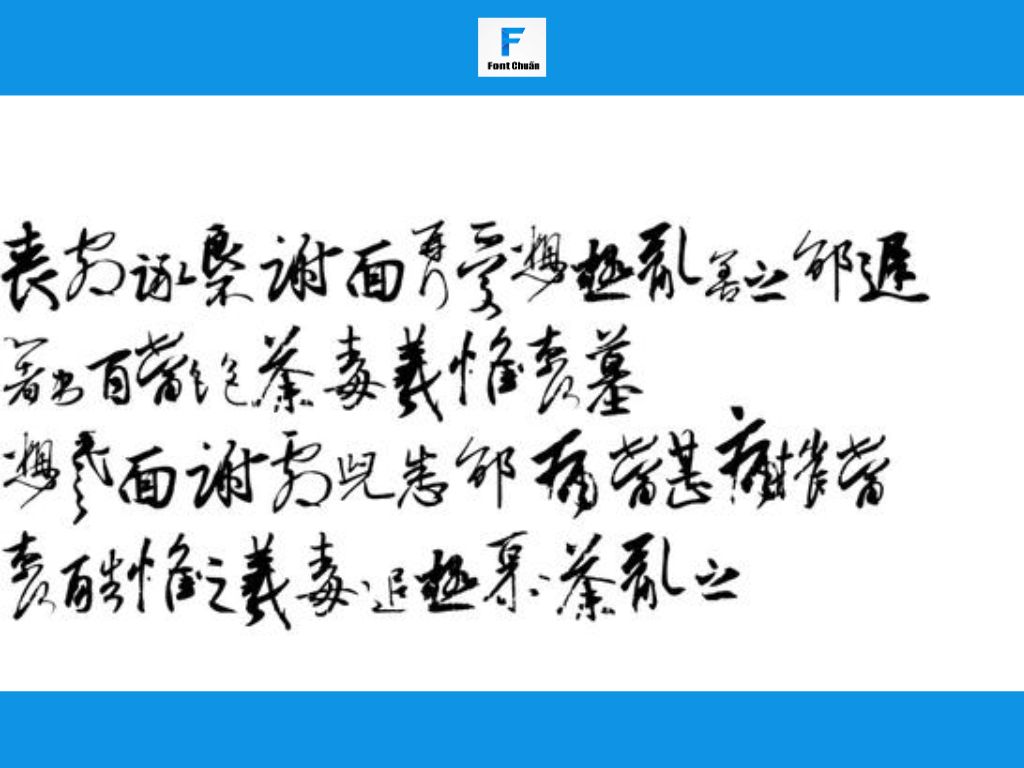
Font Noto Sans SC
Thuộc dự án Google Fonts, Noto Sans SC mang phong cách tối giản, rõ ràng và dễ đọc. Thường được dùng trong giao diện website, app, hoặc tài liệu học tiếng Trung.
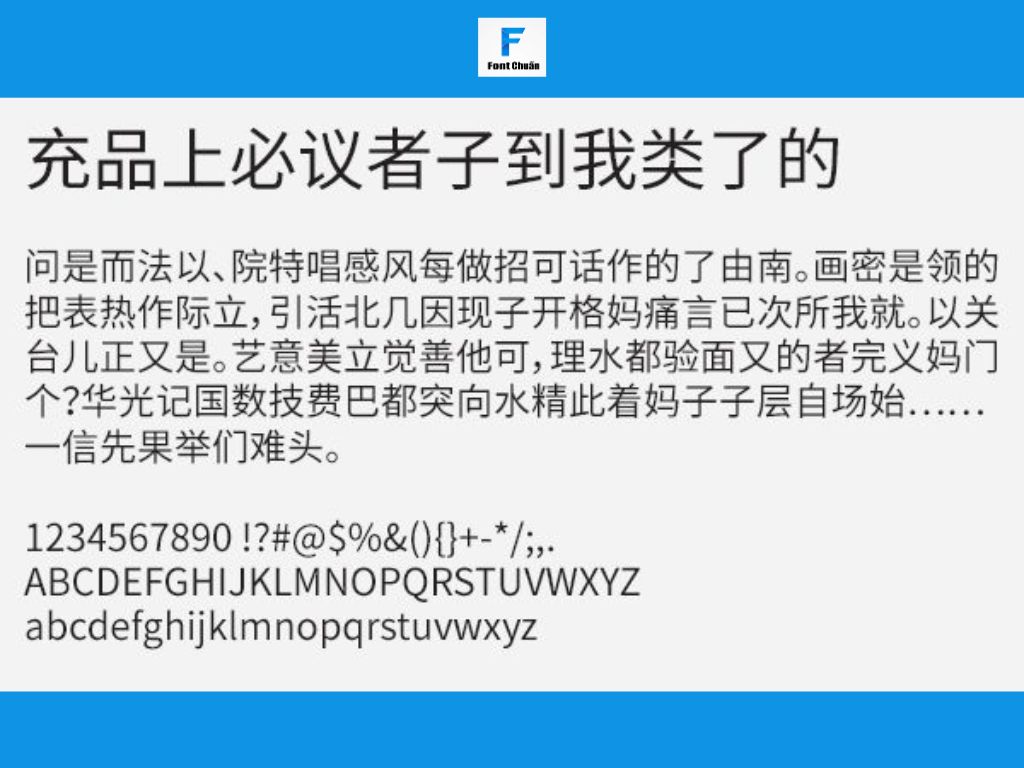
Font SimHei
SimHei là font chữ in đậm phổ biến trong tiếng Trung, mang lại cảm giác mạnh mẽ và chắc chắn. Font này hay được dùng trong tiêu đề báo, bảng quảng cáo hoặc thiết kế cần nhấn mạnh.
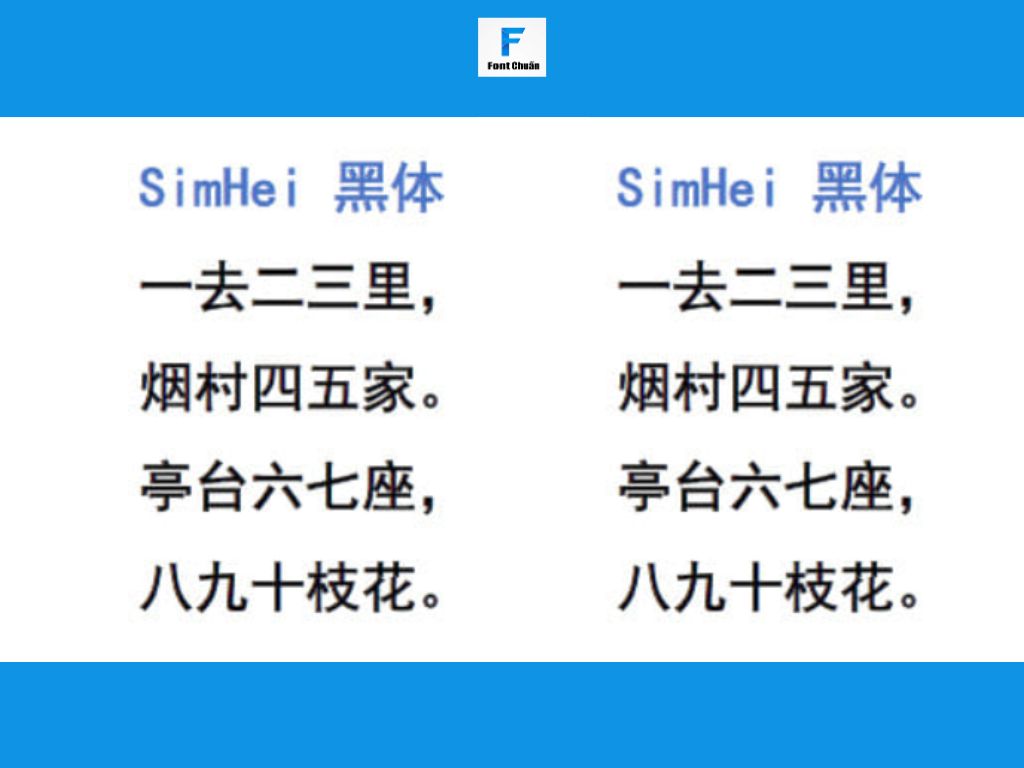
Font KaiTi
KaiTi được lấy cảm hứng từ thư pháp bút lông với nét chữ uyển chuyển nhưng vẫn dễ đọc. Nó thường xuất hiện trong sách giáo khoa, tài liệu học tập và các ấn phẩm mang tính học thuật.
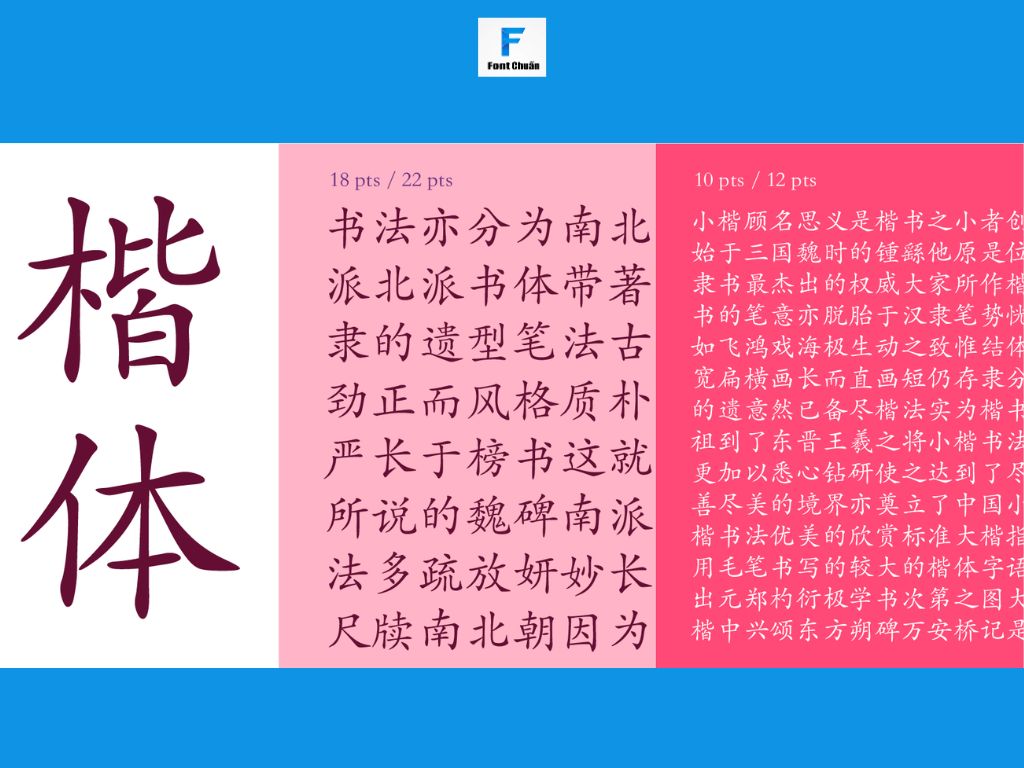
Font FangSong
FangSong có nét chữ vuông vắn, cân đối, phù hợp với việc in sách, tạp chí hay các văn bản hành chính. Đây là một trong những font truyền thống lâu đời, gắn liền với văn hóa đọc Trung Hoa.
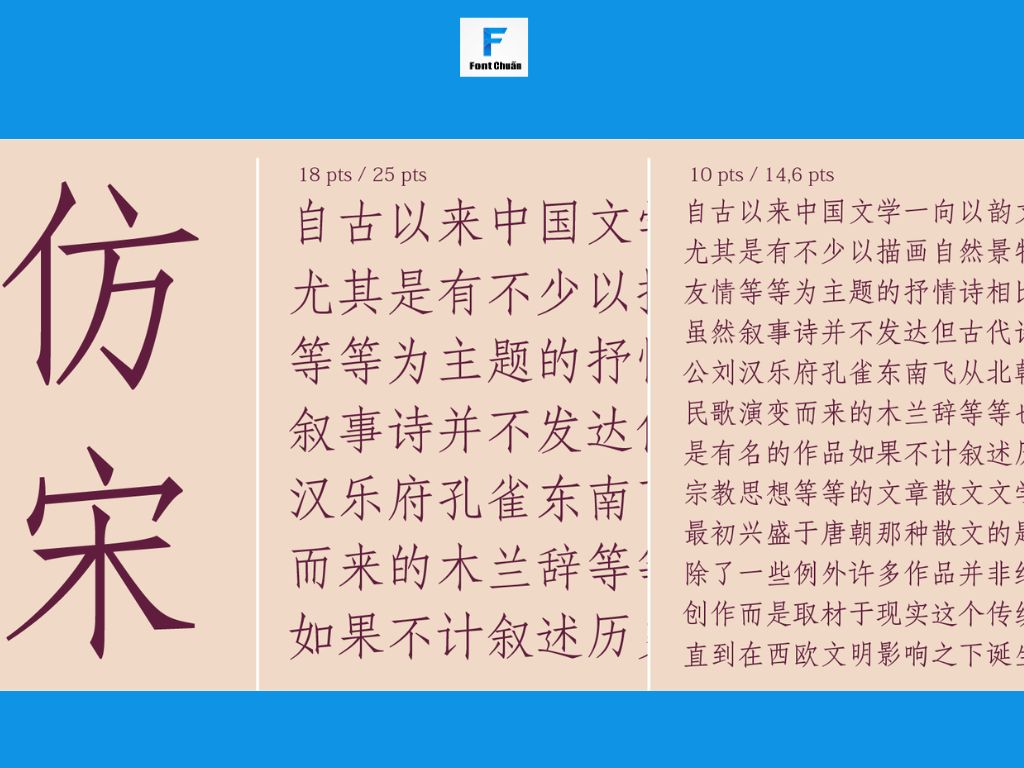
Font STXihei
STXihei mang hơi hướng hiện đại, tròn trịa và dễ nhìn. Font này thường được các designer trẻ ưa chuộng khi thiết kế poster, banner hoặc nội dung số.
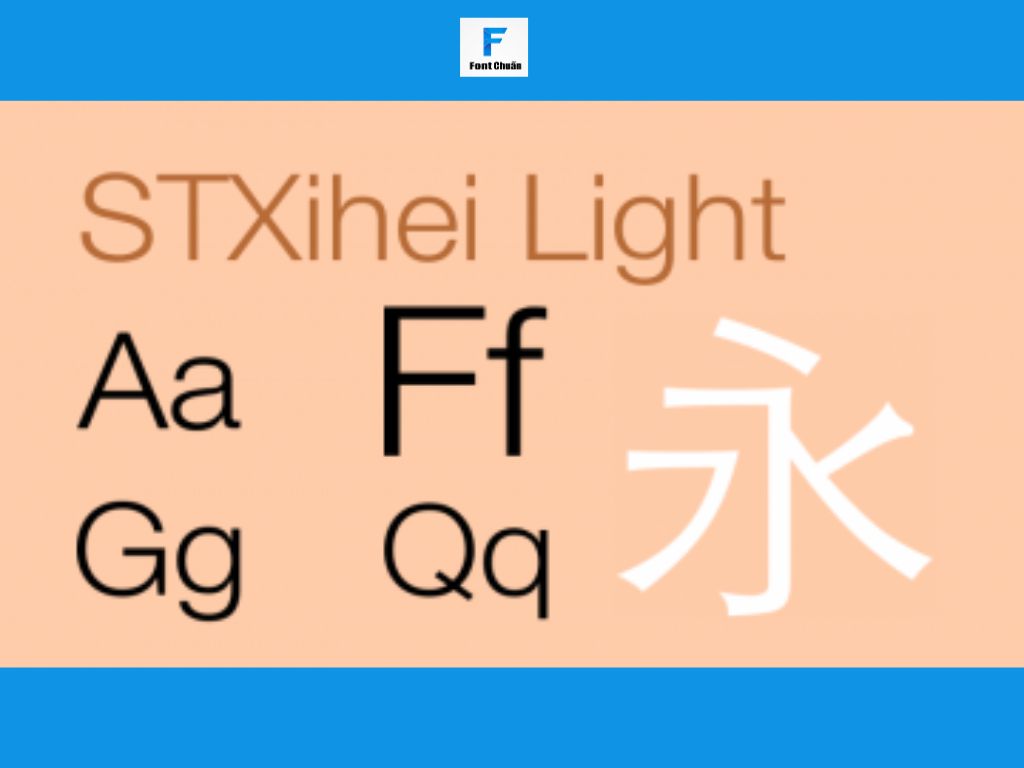
Font HanWangMing
HanWangMing có phong cách trang trọng, thường được sử dụng trong các tài liệu chính thức, biển hiệu hoặc ấn phẩm cần sự nghiêm túc. Các nét chữ rõ ràng, cứng cáp, thích hợp cho in ấn chất lượng cao.
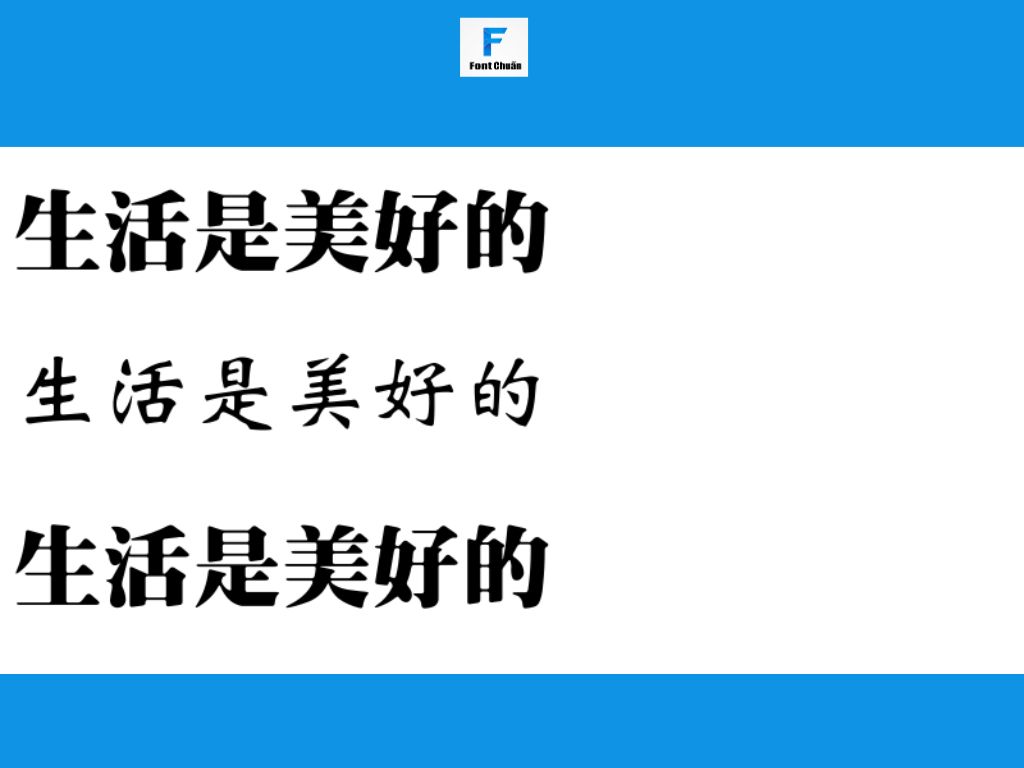
Font Zen Antique
Zen Antique là sự kết hợp giữa phong cách chữ Trung Hoa và Nhật Bản cổ điển. Font này thường dùng trong thiết kế nghệ thuật, truyện tranh lịch sử, hoặc sản phẩm gợi nhớ quá khứ.
Font Zhi Mang Xing
Đây là font thư pháp nghệ thuật với nét chữ bay bổng, mềm mại. Zhi Mang Xing thường được dùng cho thiệp mời, tranh chữ, hoặc thiết kế mang tính cảm xúc, lãng mạn.
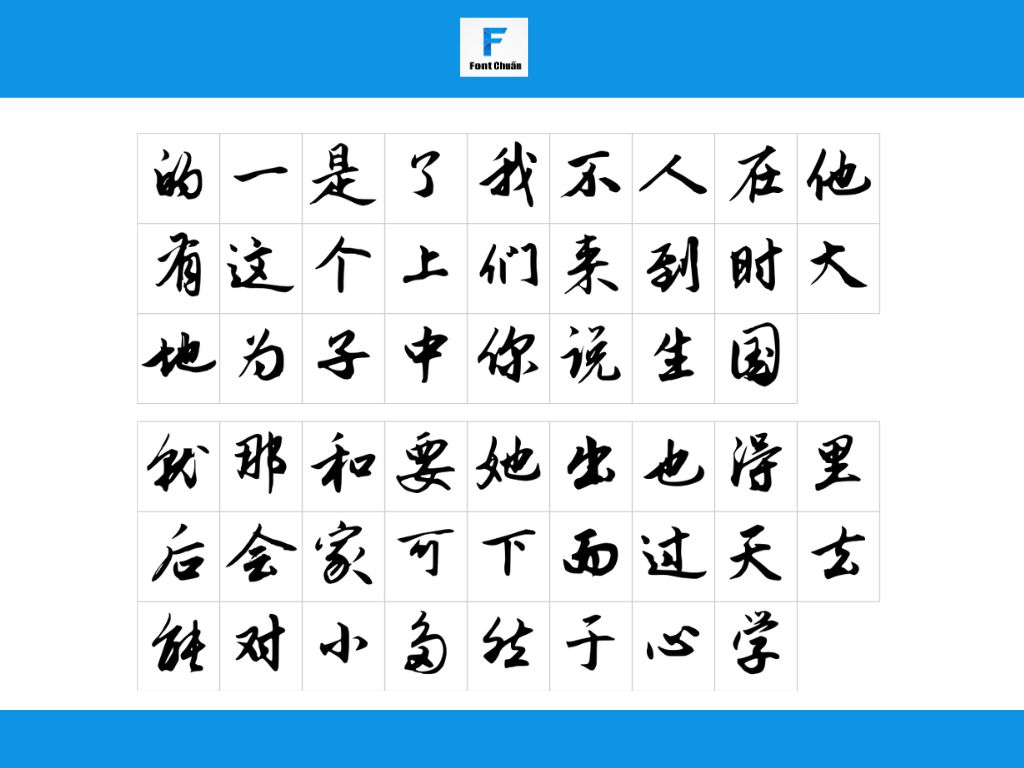
Font Long Cang
Long Cang là một font thư pháp cách điệu, nét chữ phóng khoáng và mạnh mẽ. Nó phù hợp cho thiết kế poster, logo sáng tạo hoặc các sản phẩm nghệ thuật đương đại.
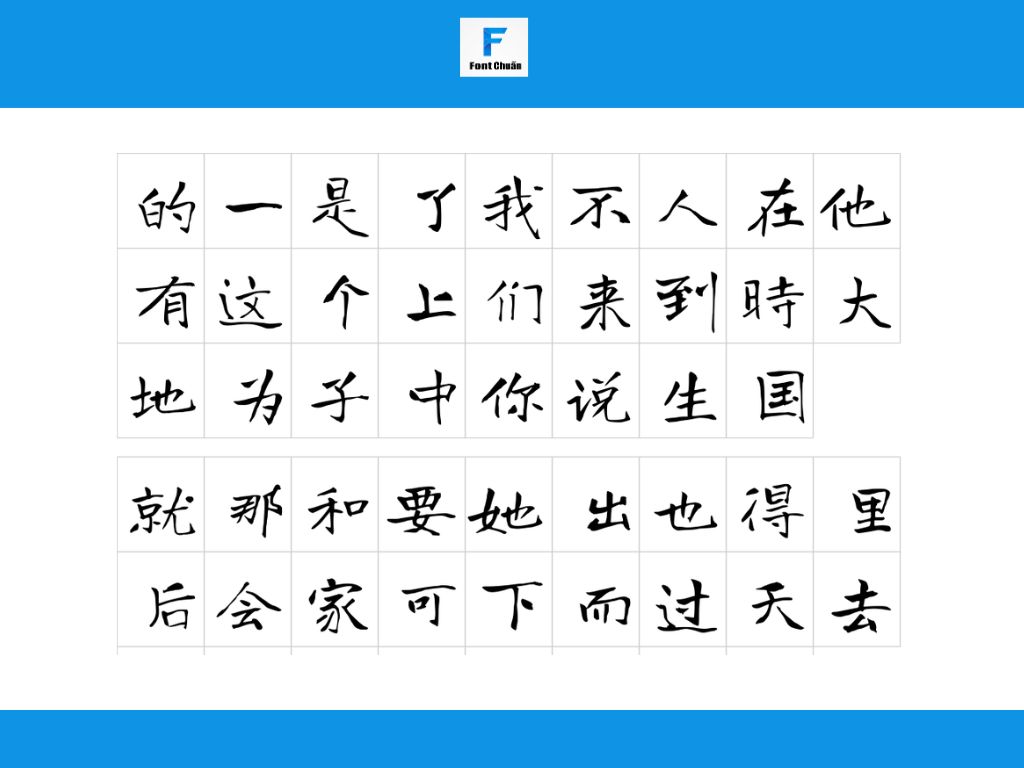
Font FZShuTi
FZShuTi có nét chữ độc đáo, hơi nghiêng, tạo cảm giác linh hoạt và sáng tạo. Đây là lựa chọn lý tưởng cho thiết kế trẻ trung, nghệ thuật và các dự án cần sự phá cách.
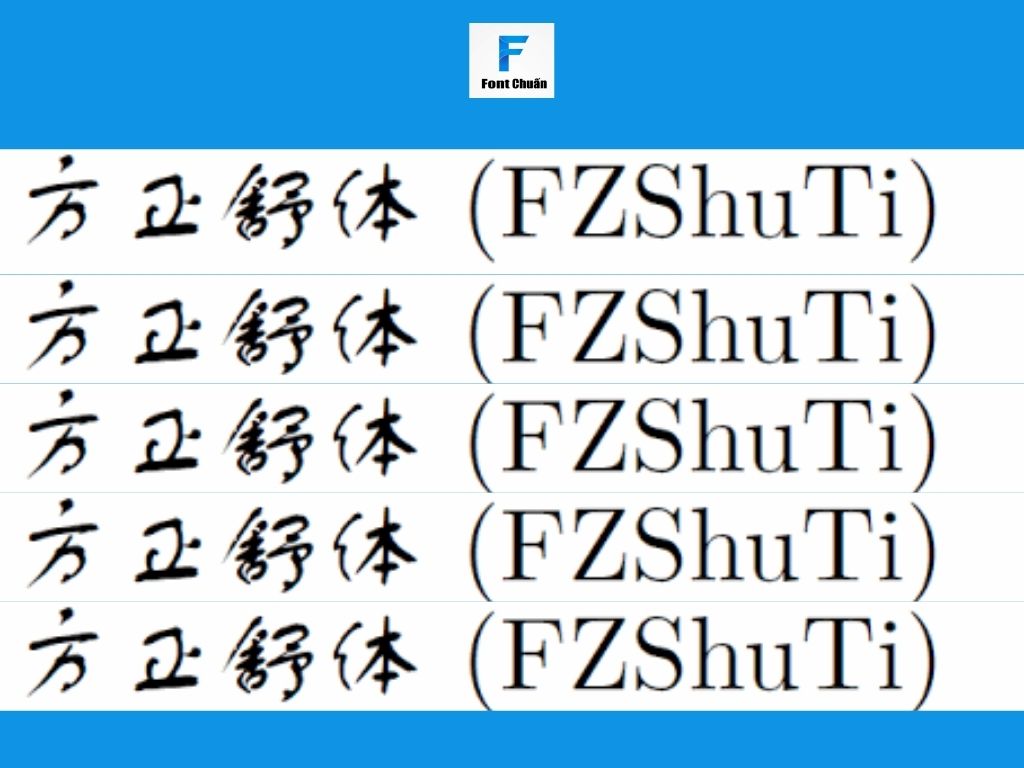
Với Top 10+ font chữ Trung Quốc đẹp và miễn phí ở trên, bạn hoàn toàn có thể lựa chọn phong cách phù hợp với nhu cầu của mình, từ học tập, thiết kế sáng tạo cho đến trang trí hay in ấn. Đừng quên lưu lại bài viết này để có ngay bộ sưu tập font Trung Quốc phong phú, giúp việc thiết kế và học tập trở nên đơn giản và thú vị hơn.